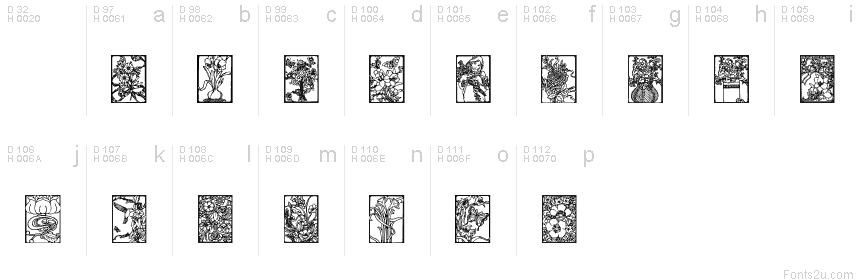
Art Nouveau Flowers di House of Lime è un font decorativo gratuito ispirato alla natura. Ogni glifo è una vera e propria illustrazione in miniatura: pannelli verticali slanciati ricchi di steli sinuosi, petali in fiore e viticci intricati, dal tratto che sembra disegnato a mano e leggermente selvaggio. Il design in bianco e nero evoca l'atmosfera delle vetrate — decorato ma ordinato — permettendoti di inserire un singolo simbolo per ottenere istantaneamente un'elegante cornice o un motivo Art Nouveau, senza dover disegnare nulla.
Con Art Nouveau Flowers, puoi arricchire rapidamente partecipazioni di nozze, copertine di libri, etichette, poster, packaging o grafiche per i social che richiedono un tocco botanico rigoglioso. Questo font gratuito funziona a meraviglia come bordo, illustrazione o separatore decorativo piuttosto che come testo. Per una composizione equilibrata, abbina questi dettagliati elementi floreali a un font sans serif geometrico pulito e mantieni i dingbat abbastanza grandi, in modo che le curve sottili e le foglie restino nitide sia in stampa che a schermo.